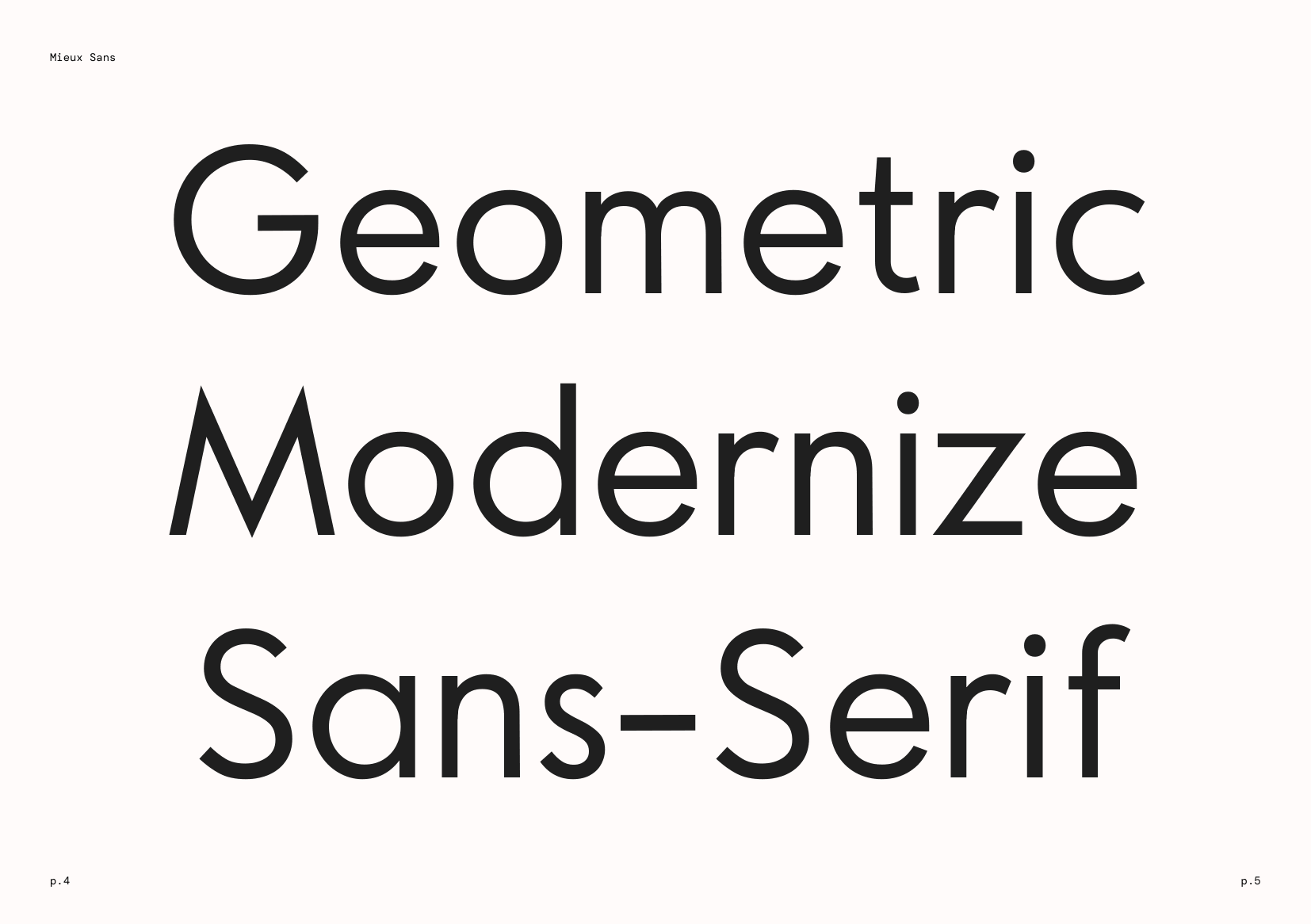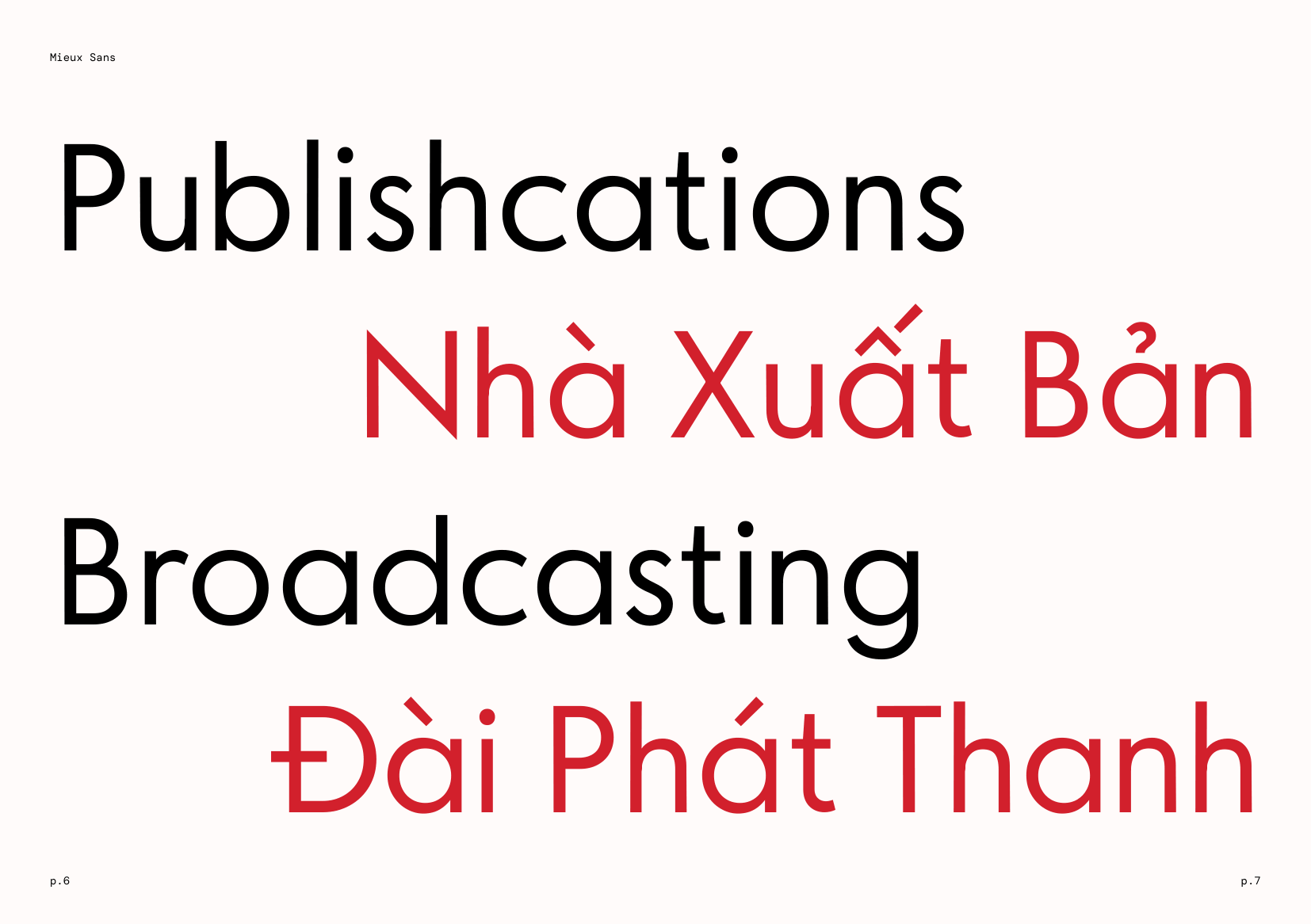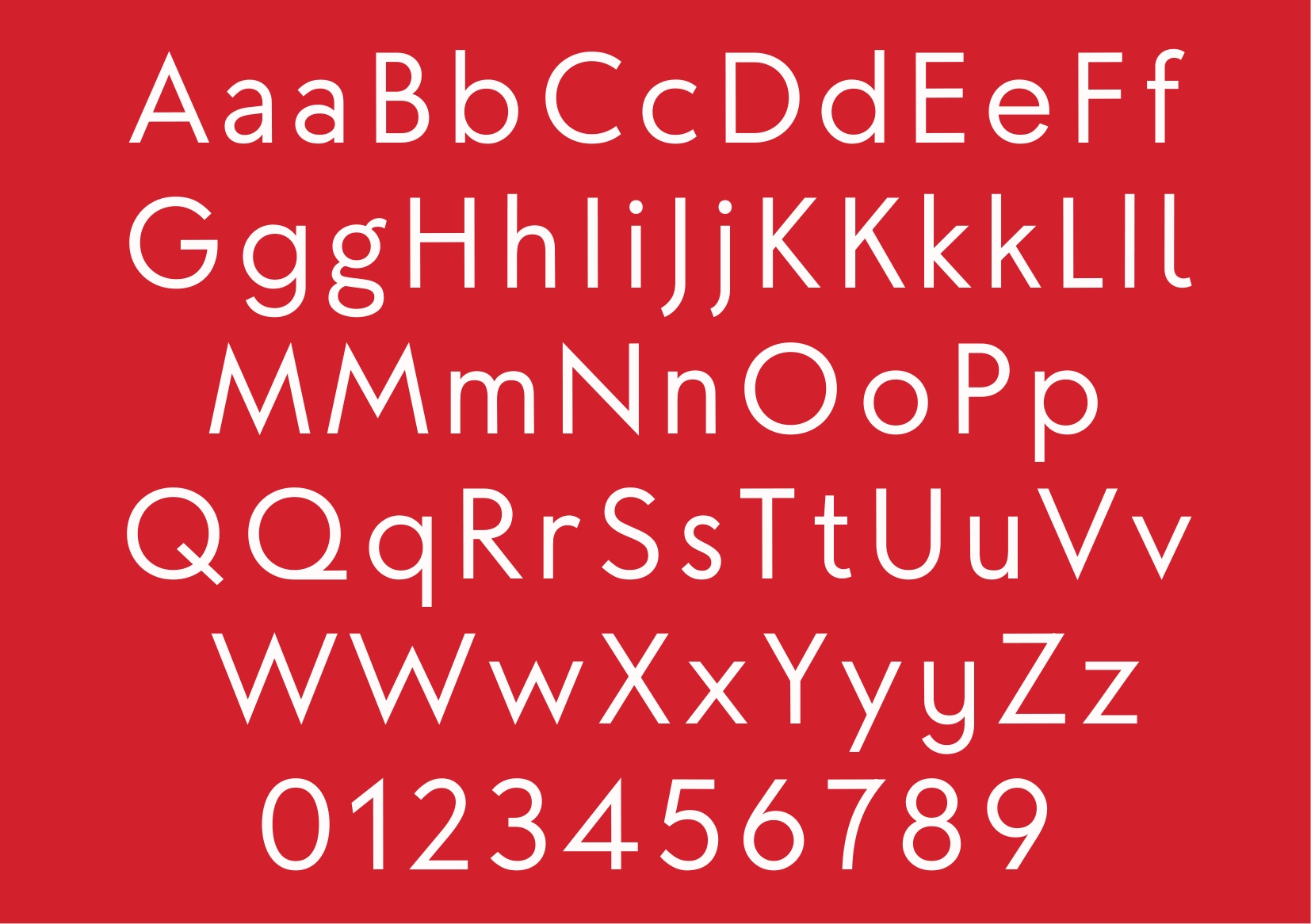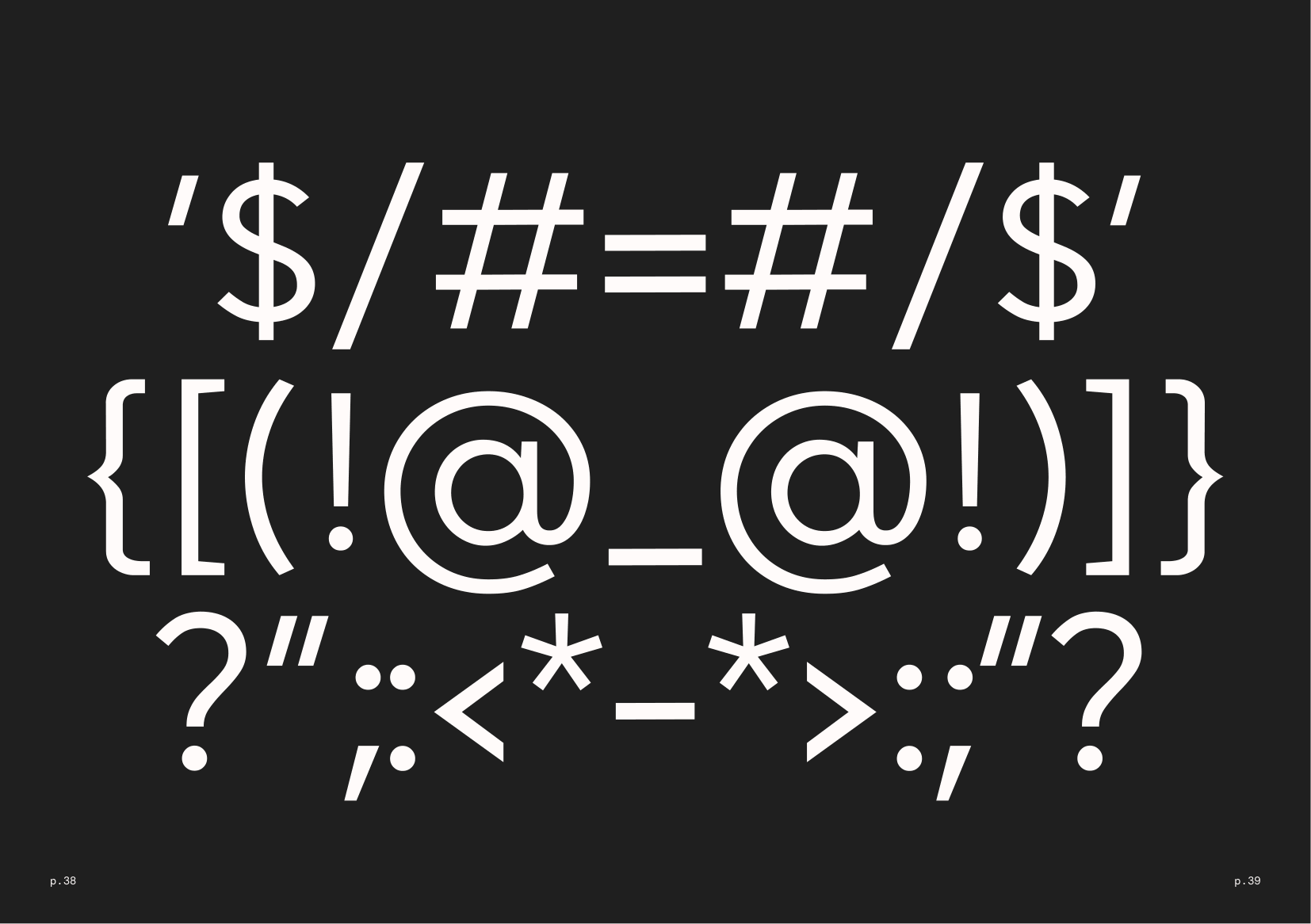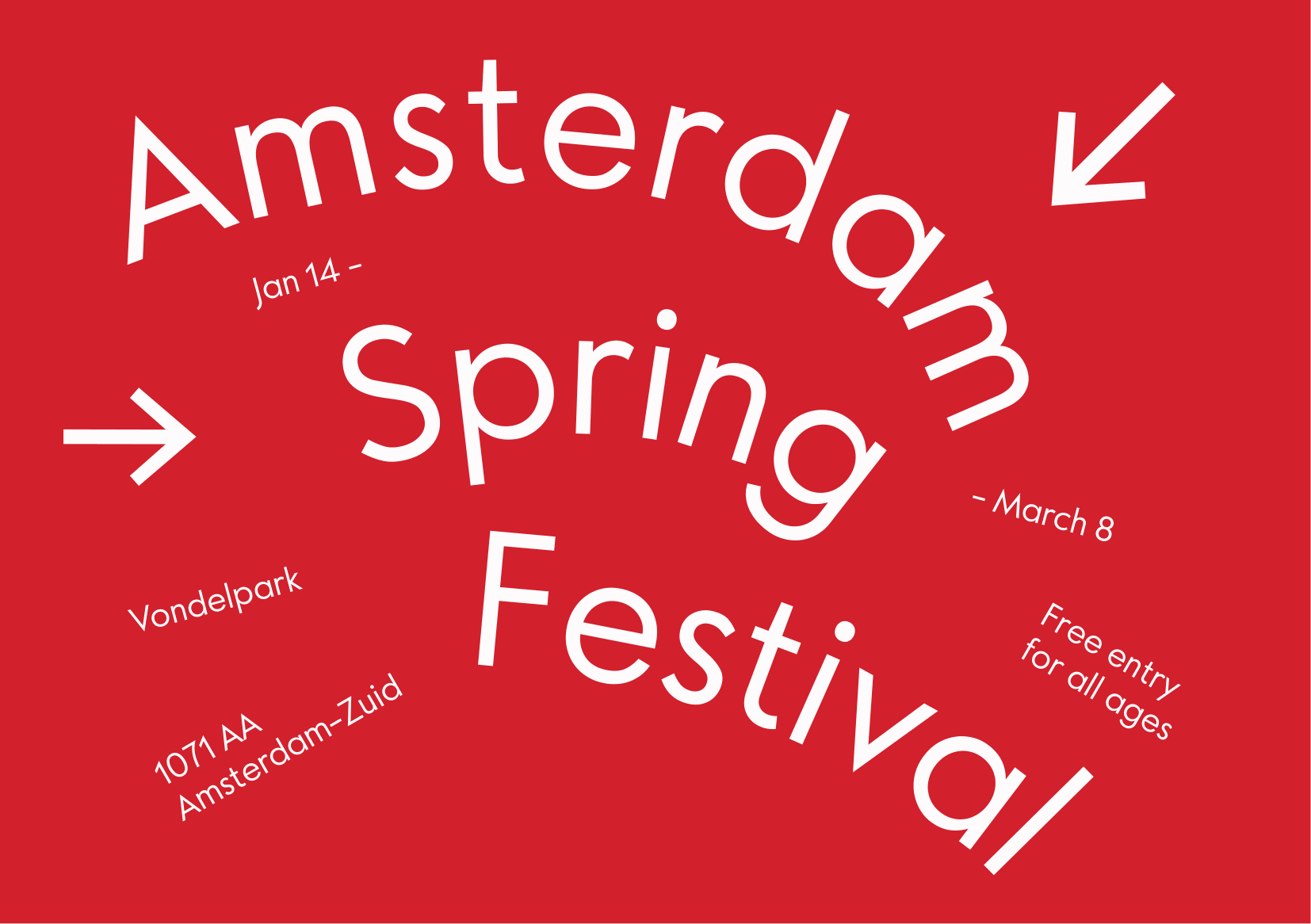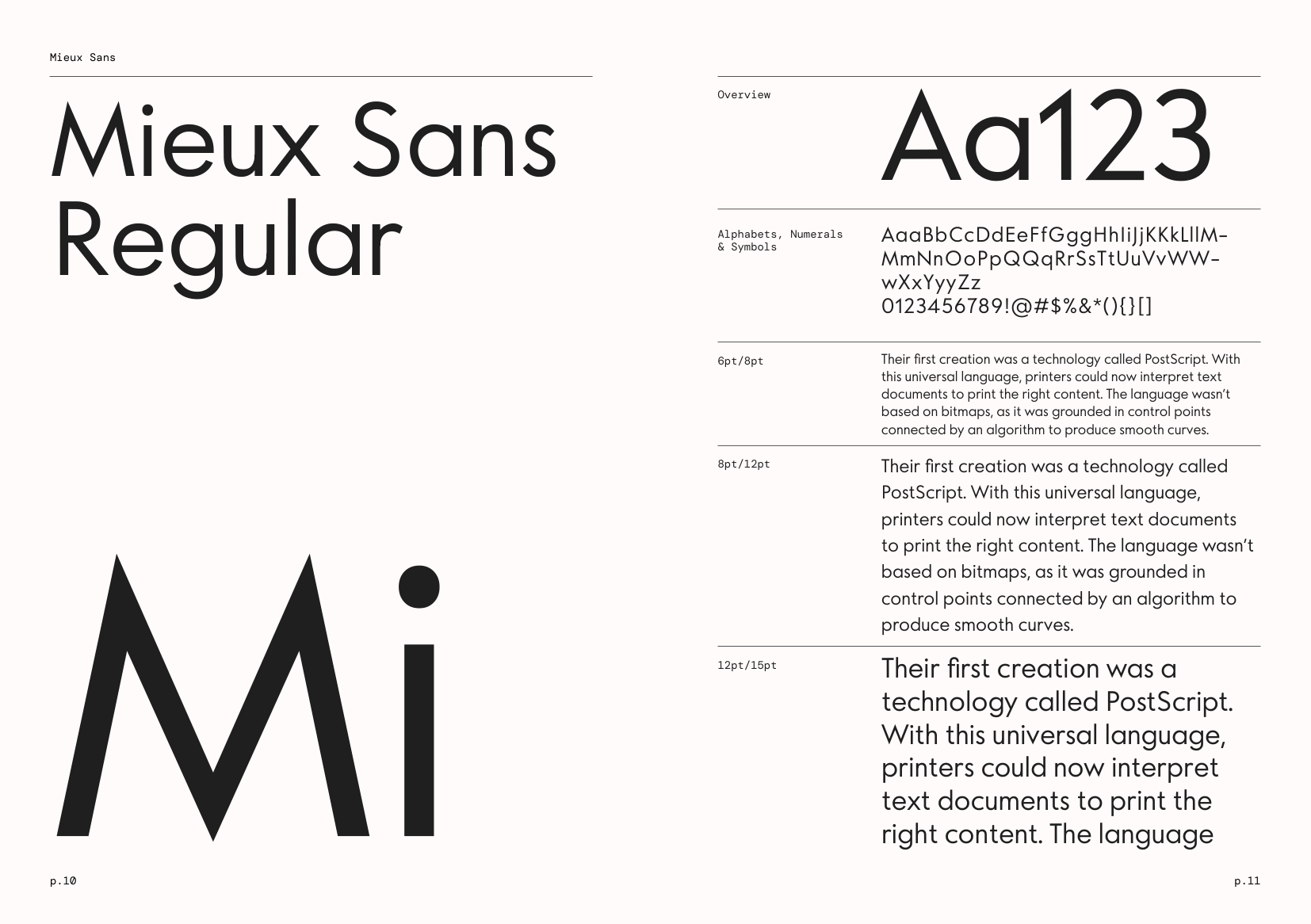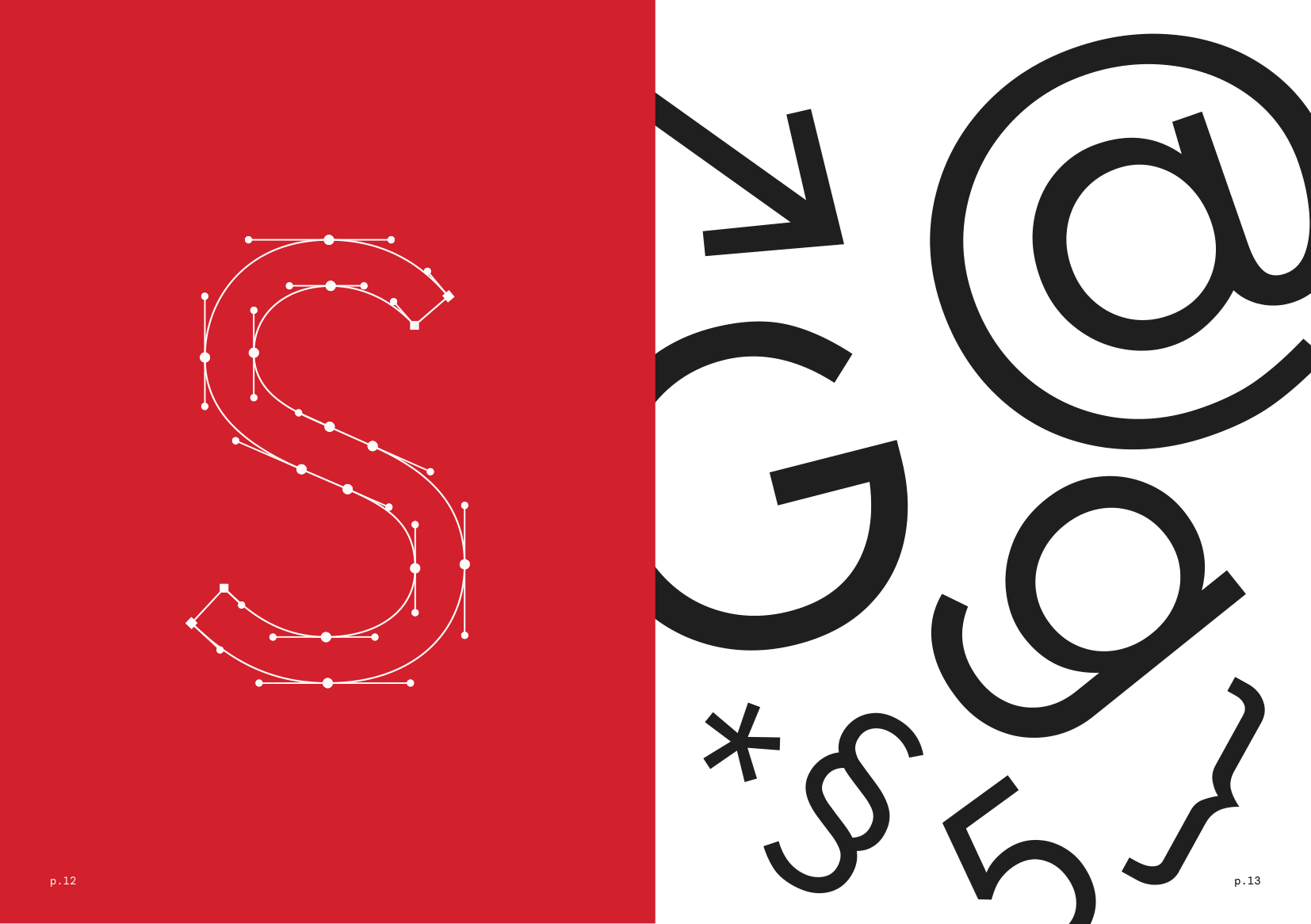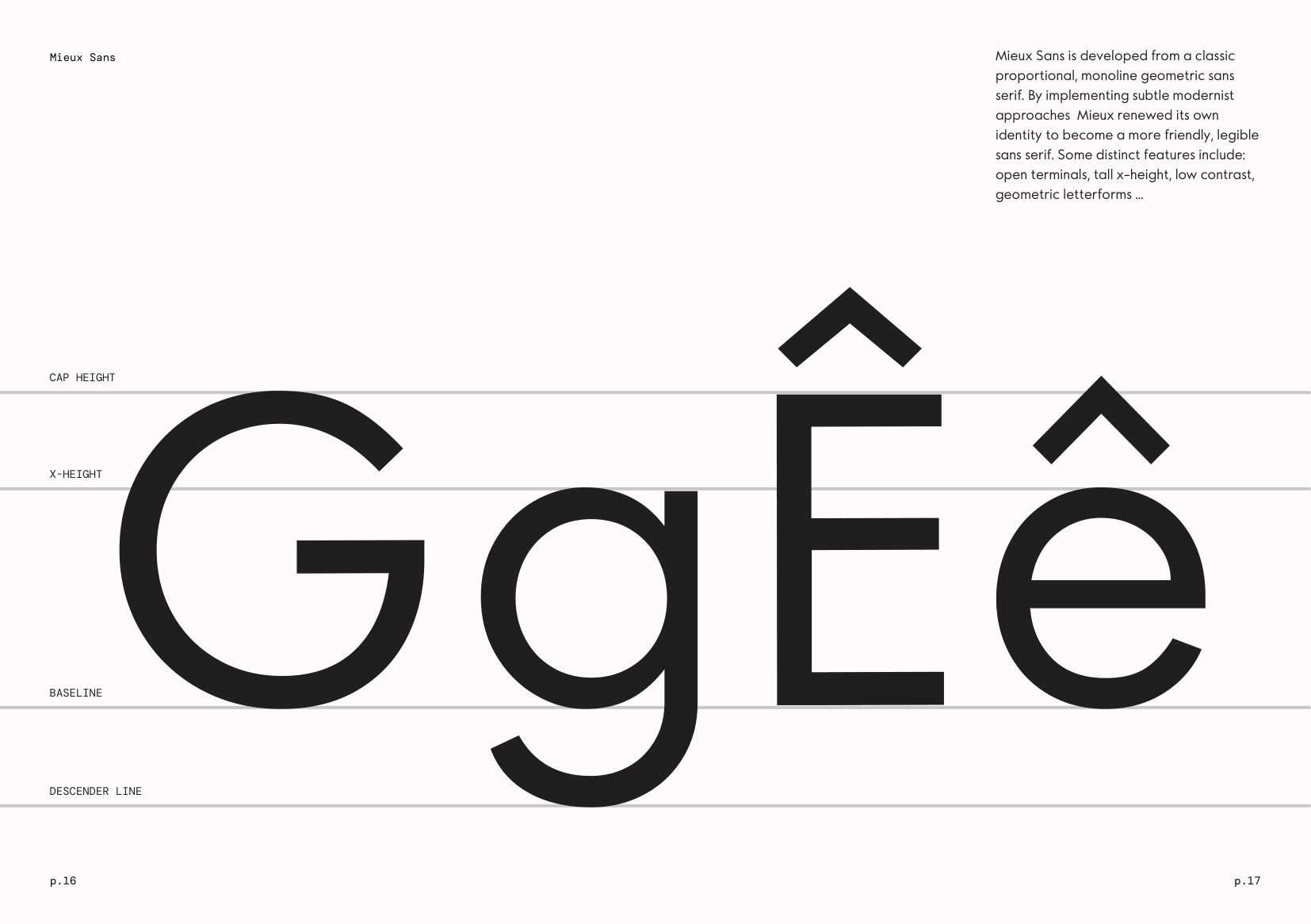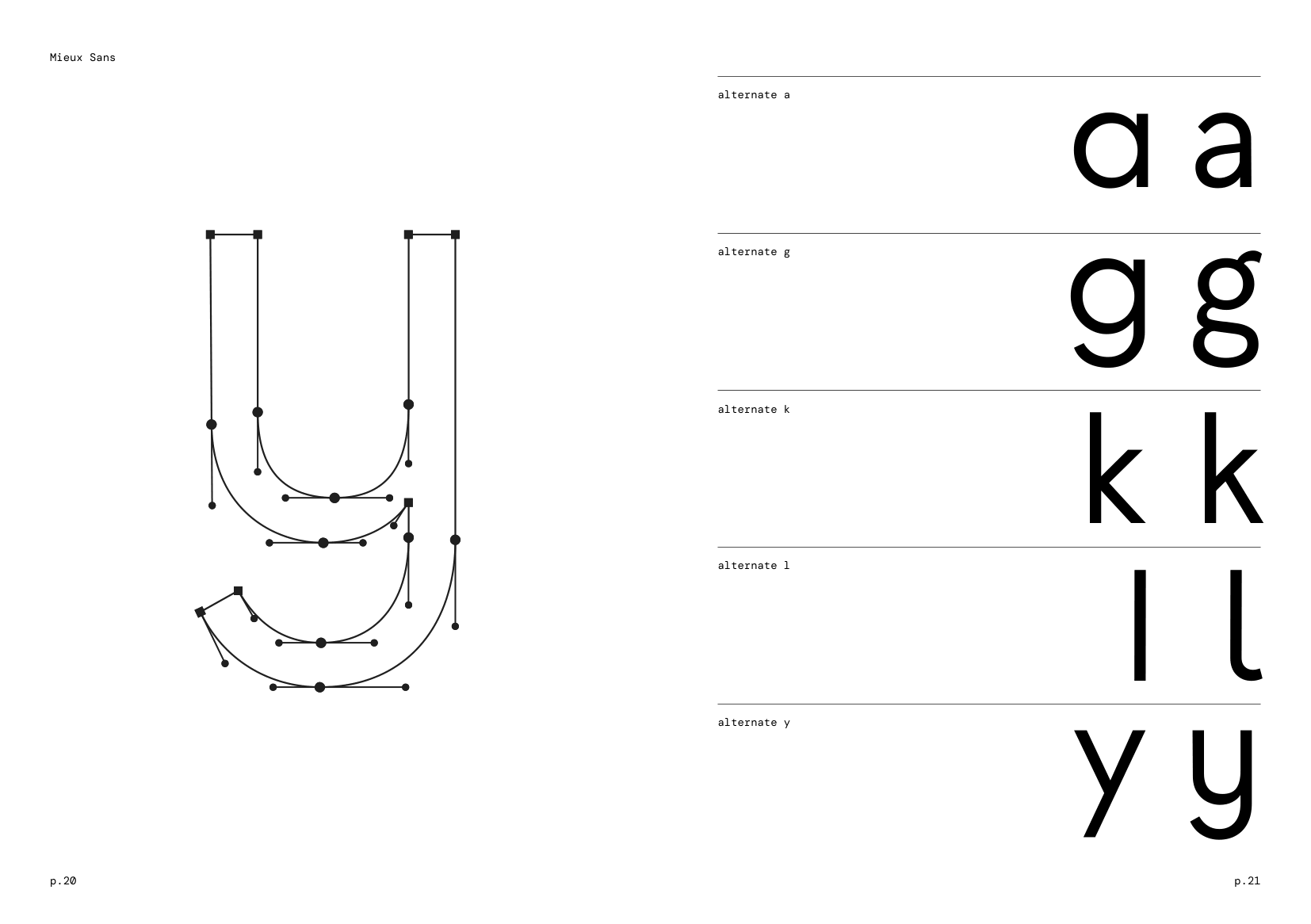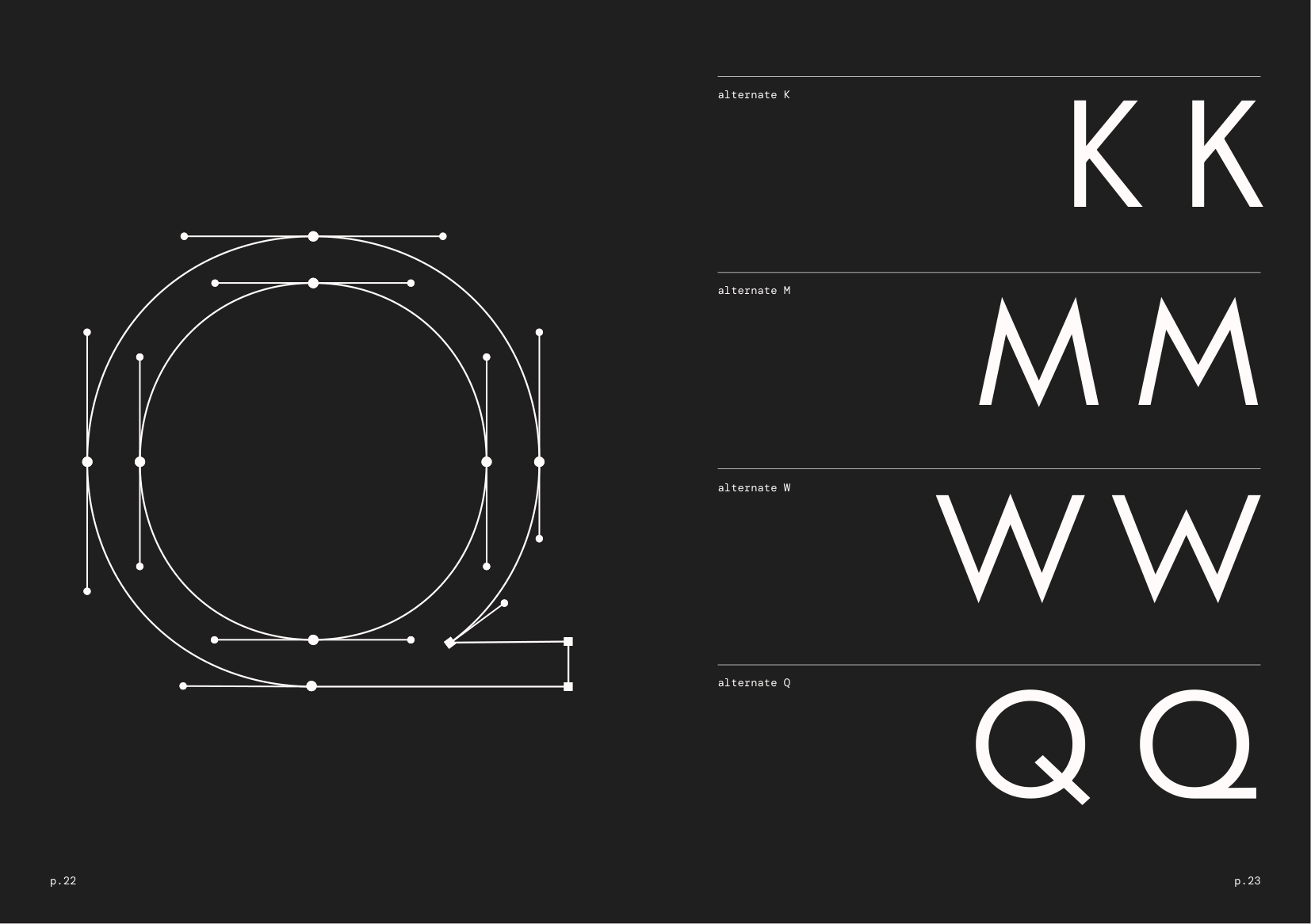
Mieux
Về Mieux: Mieux là một kiểu chữ sans serif hình học, lấy cảm hứng từ Europe, một kiểu chữ được phát triển bởi xưởng đúc chữ Deberny & Peignot, lần đầu ra mắt vào năm 1937 như một phiên bản tiếng Pháp của Futura. Mieux thể hiện một hướng tiếp cận hiện đại hơn, chú trọng vào tính dễ đọc và khả năng đọc hiểu của kiểu chữ sans serif hình học, cũng như khả năng thích ứng với kỷ nguyên kỹ thuật số ngày nay.
Geometric Sans-serif
Text
Mieux
Xuất Bản
Mieux
Broadcasting
Mieux
Văn Nghệ
Mieux
Contemporary Perspective
Europe is not an original typeface in the traditional sense — it is the French identity given to Futura, the landmark geometric sans-serif designed by Paul Renner and released by the German Bauer foundry in 1927.
Charles Peignot and Maximilien Vox acquired the rights to distribute Futura under the name "Europe", the new name being chosen by Charles Peignot himself, with distribution limited to France, the French colonies, and select countries including Egypt, Syria, Turkey, Greece, and French-speaking Switzerland. The decision to license the typeface came from a sense of urgency within the foundry. Maximilien Vox was deeply concerned about the absence of a modern typeface that could respond to the new demands of advertising, and he pushed so strongly for the acquisition of Futura that he offered his resignation to the board of directors if the foundry did not act immediately.